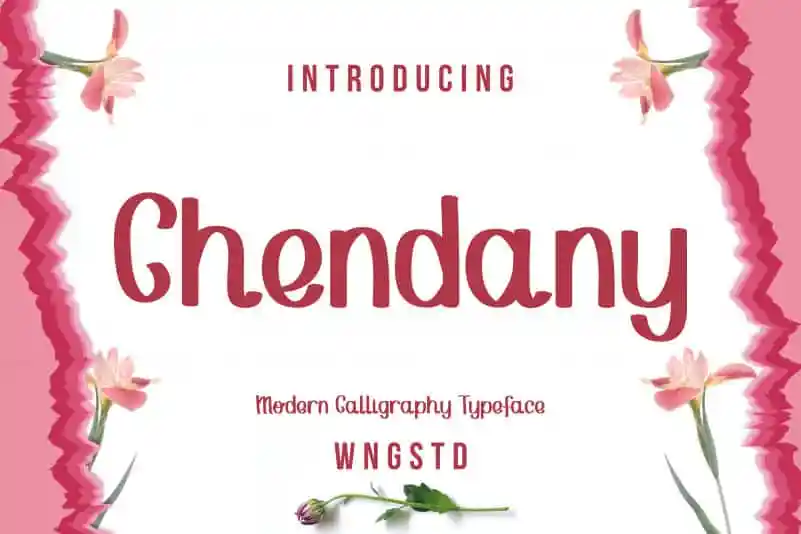
Chendany – Modern Script typeface – Download Grátis
Chendany é uma fonte moderna e desenhada com um toque leve que brilha especialmente quando aplicada a texturas antigas ou decorações contemporâneas. Essa fonte foi criada para trazer vida à escrita, adaptando-se de maneira perfeita tanto ao ambiente tradicional quanto à web. Seu design curvilíneo e moderno faz dela uma opção excelente para designers gráficos e criadores artísticos que desejam dar um toque atraente às suas criações. Completamente compatível com todos os sistemas de criação, Chendany é perfeita tanto para projetos tradicionais quanto para o web design. Seu charme despojado torna-a uma escolha ótima não apenas para identidades visuais inspiradoras e posters criativos, mas também para comunicação em diferentes plataformas digitais. Com Chendany à sua disposição, pode transformar qualquer projeto em um verdadeiro ato de arte.
Designer: WNGSTD